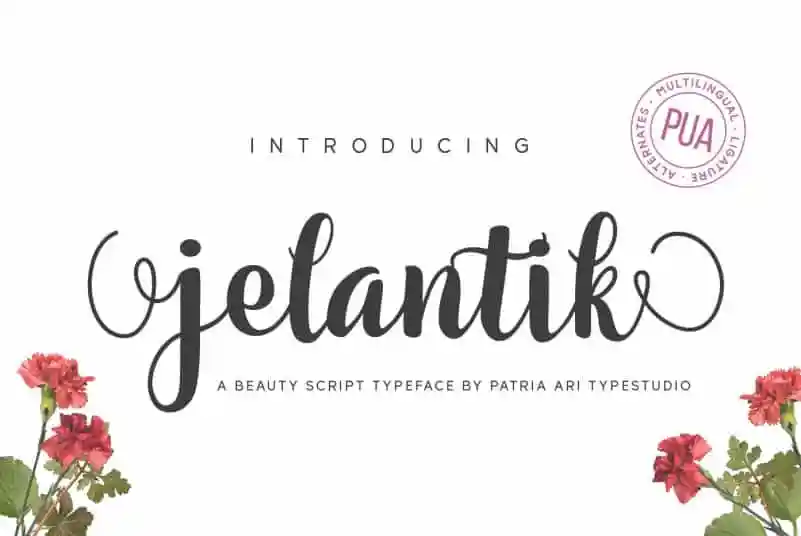
Jelantik Script Font – Download Grátis
A Jelantik Script Font é uma elegante tipografia script com traços cíferis adoráveis que se destacam por sua simplicidade e alegria. Perfeita para projetos de marca, logotipos, convites de casamento, postagens nas redes sociais, anúncios, embalagens de produtos, designs dos produtos, etiquetas, fotografias, marcas digitais, convites e cartões-postais, a Jelantik traz um toque autêntico do papel da vida. Esta fonte de script oferece uma sensação única que pode enriquecer qualquer projeto onde haja um gosto por escrita à mão. Com sua rica versatilidade, a Jelantik é perfeita para estilos modernos e clássicos em projetos variados do design gráfico.